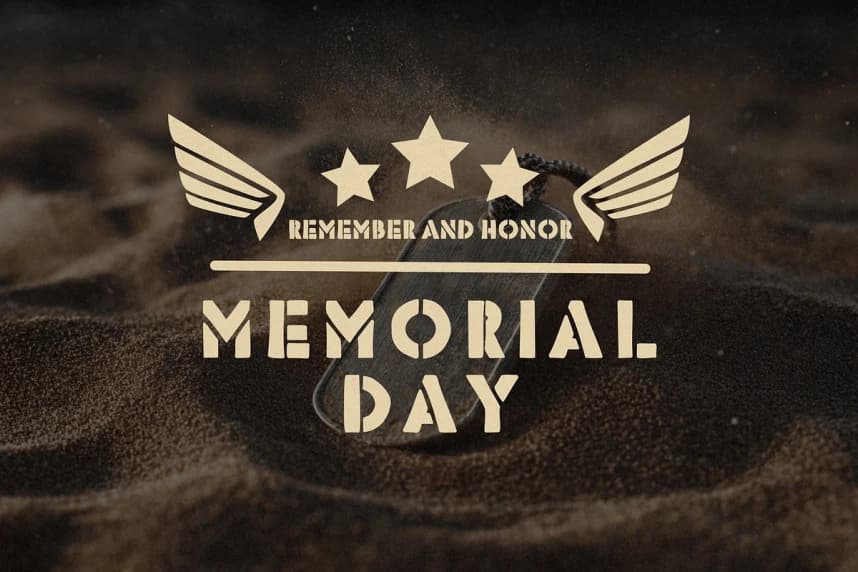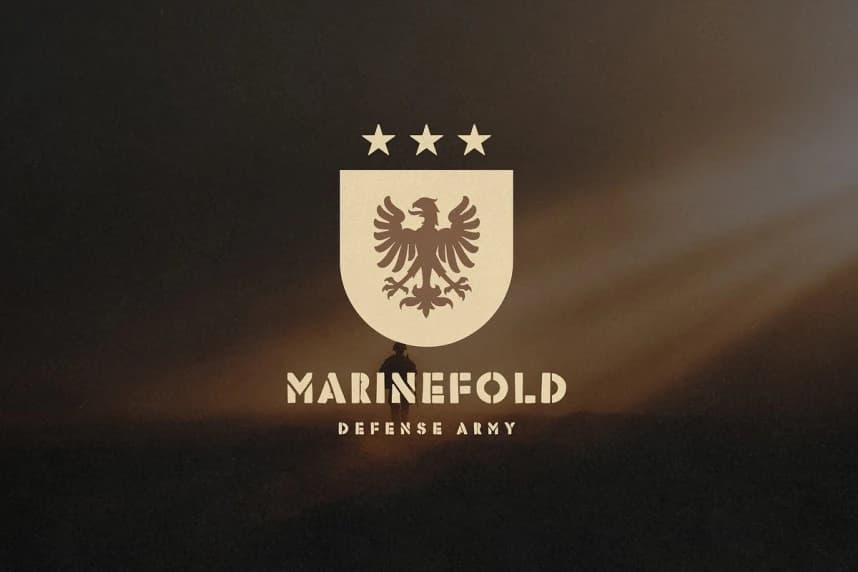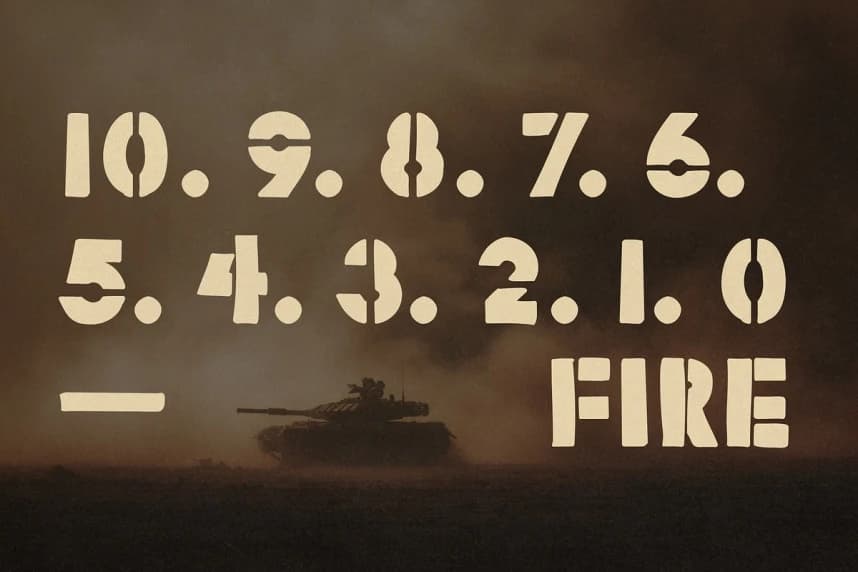
Stencil Force Font
Stencil Force Font, dikkat çekmek için tasarlanmış, zorlu ve savaş testinden geçmiş bir askeri fonttur. Kutu, araç ve teçhizat üzerinde kullanılan gerçek dünya askeri stencil'lerinden ilham alınmıştır. Tüm harfleri büyük olan bu font, otantik sertliği modern bir dokunuşla sunar.
Stencil Force Font, dikkat çekmek için tasarlanmış, zorlu ve savaş testinden geçmiş bir askeri fonttur. Kutu, araçlar ve ekipmanlarda kullanılan gerçek dünya askeri şablonlardan ilham alınmıştır; tüm harflerin büyük yazıldığı bu güç, otantik sertliği modern bir dokunuşla sunar.